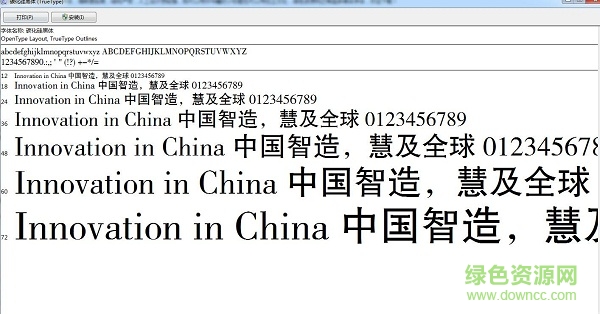
碳化硅黑體 普通
碳化硅黑體字體是一款普通的黑體字體,清晰度較高,結(jié)構(gòu)嚴(yán)密,人工設(shè)計(jì)感較強(qiáng),既可以用作書籍的小標(biāo)題也可以用在正文處,綠色資源網(wǎng)還有超多黑體字體,歡迎下載!
黑體字體特征
1.沒有襯線裝飾,
2.筆劃挺拔有力,撇捺等筆畫不尖,
3.筆畫橫平豎直,筆跡全部一樣粗細(xì),
4.常用于標(biāo)題,導(dǎo)語(yǔ),標(biāo)志等等。